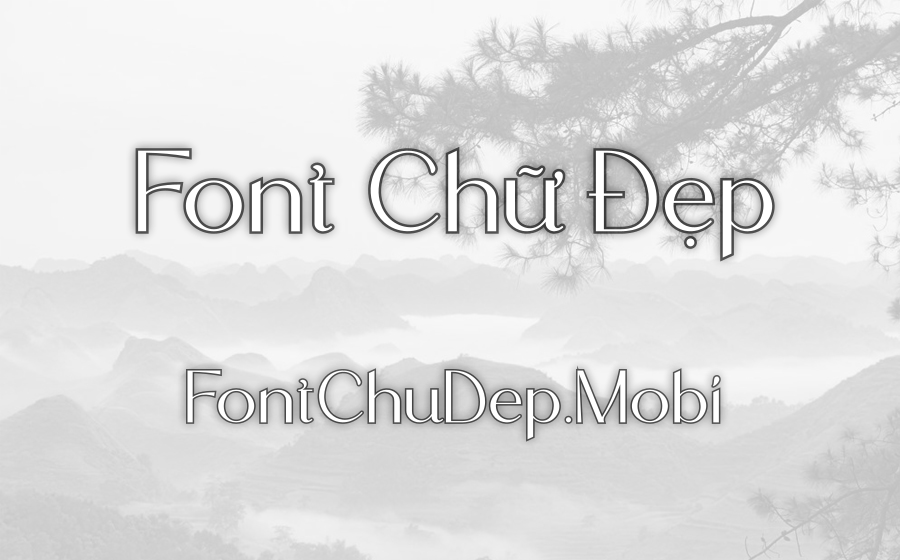
Font SVN Archattes Việt Hóa
SVN Archattes
Archattes là một font chữ sans-serif đầy mê hoặc mà tôi đã có cơ hội trải nghiệm gần đây. Với sự kết hợp hoàn hảo giữa nét thanh thoát và vẻ đẹp hiếm có, font chữ này thực sự tạo nên một bầu không khí sang trọng cho bất kỳ ai đang tìm cách thể hiện ý tưởng sáng tạo của mình. Dù là gửi đi thiệp mời, phát triển thương hiệu, hay thiết kế nhãn mác, Archattes đều mang đến một hơi thở hiện đại và tinh tế, đồng thời thể hiện sự chuyên nghiệp và cuốn hút.
Đi sâu vào đặc điểm thiết kế, Archattes nổi bật với các đường nét tinh tế, gọn gàng và dễ đọc, rất phù hợp cho những ứng dụng như thiết kế logo, nghệ thuật nhiếp ảnh, và cả một loạt các dự án sáng tạo khác. Trong lĩnh vực quảng cáo, thiết kế đồ họa, xây dựng thương hiệu, font chữ này thực sự tỏa sáng và tạo nên dấu ấn riêng biệt. Với Archattes, mỗi thiết kế đều trở nên đầy cảm hứng và khác biệt.